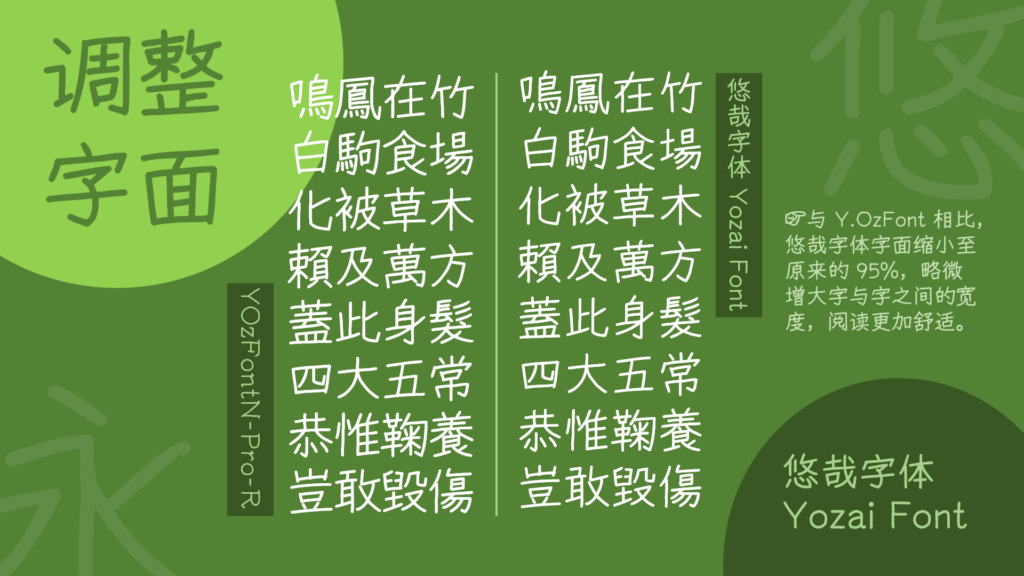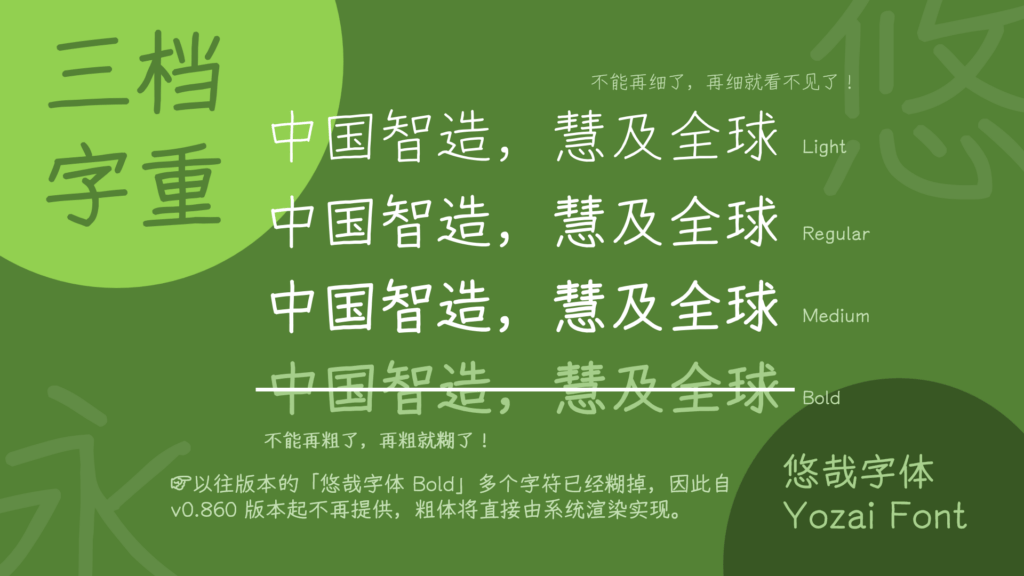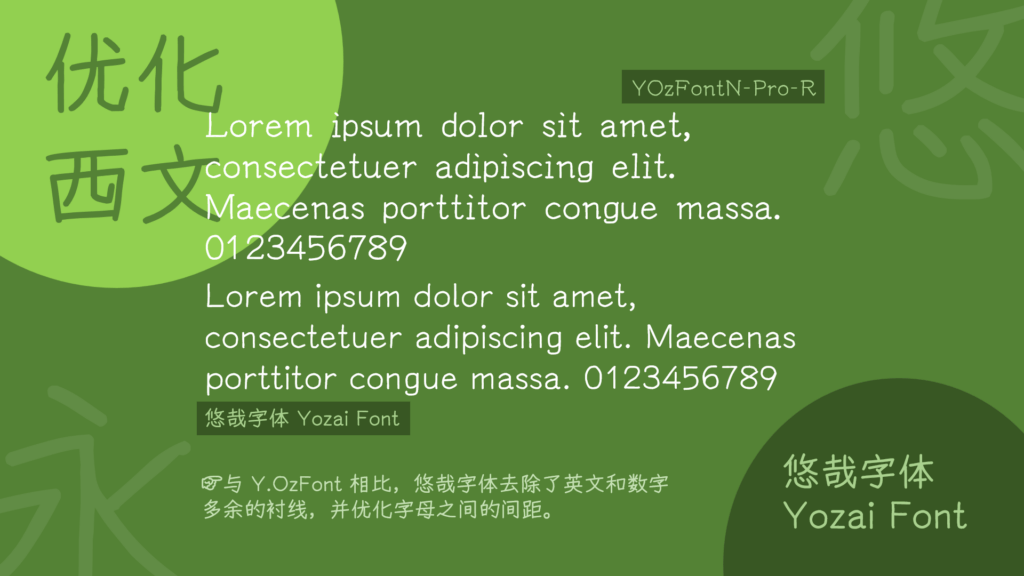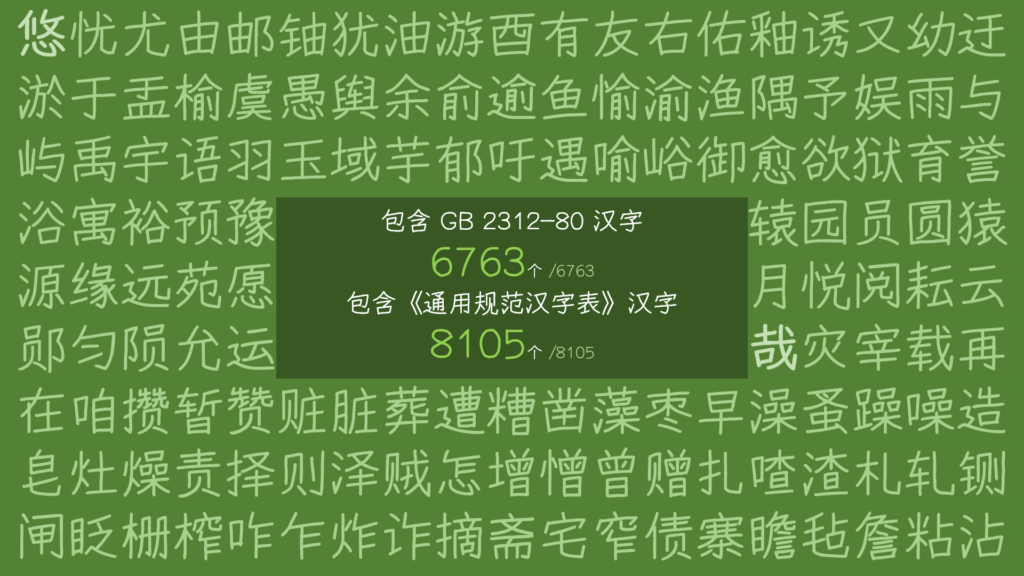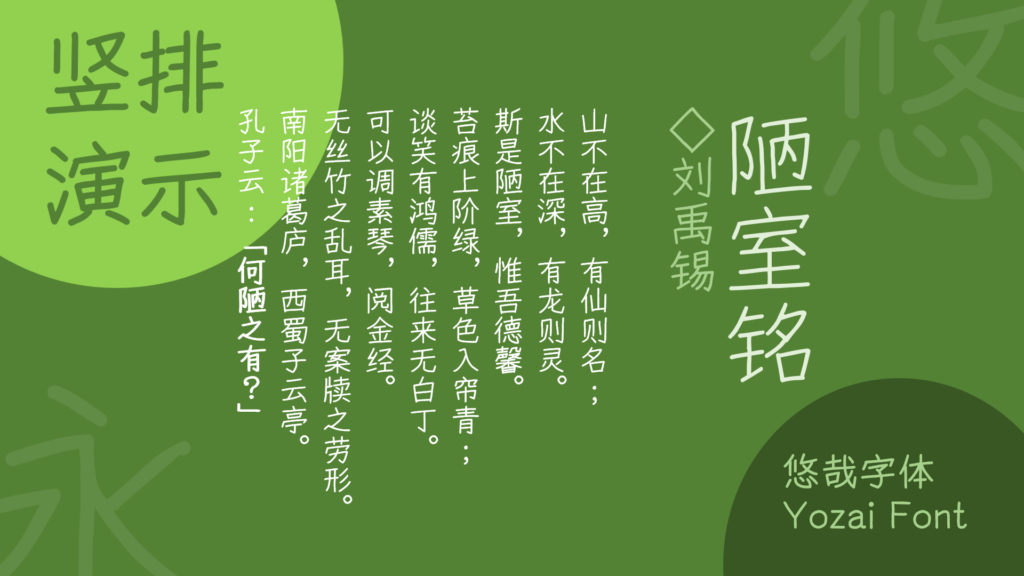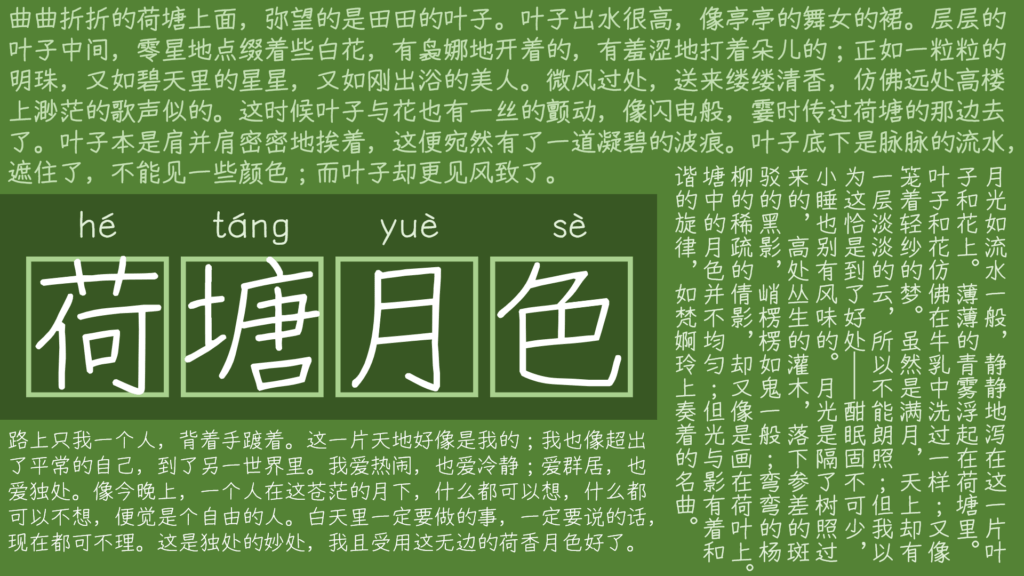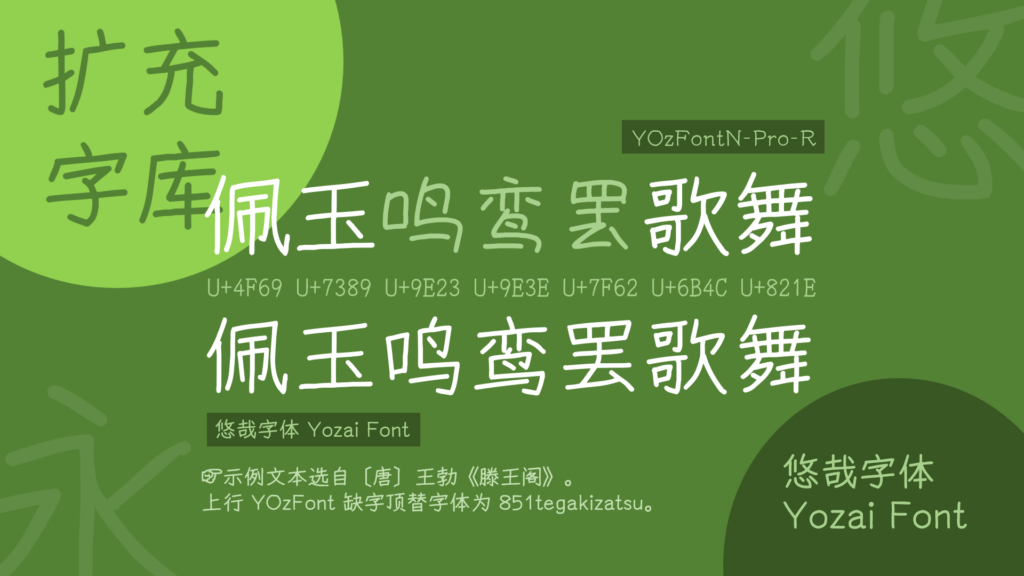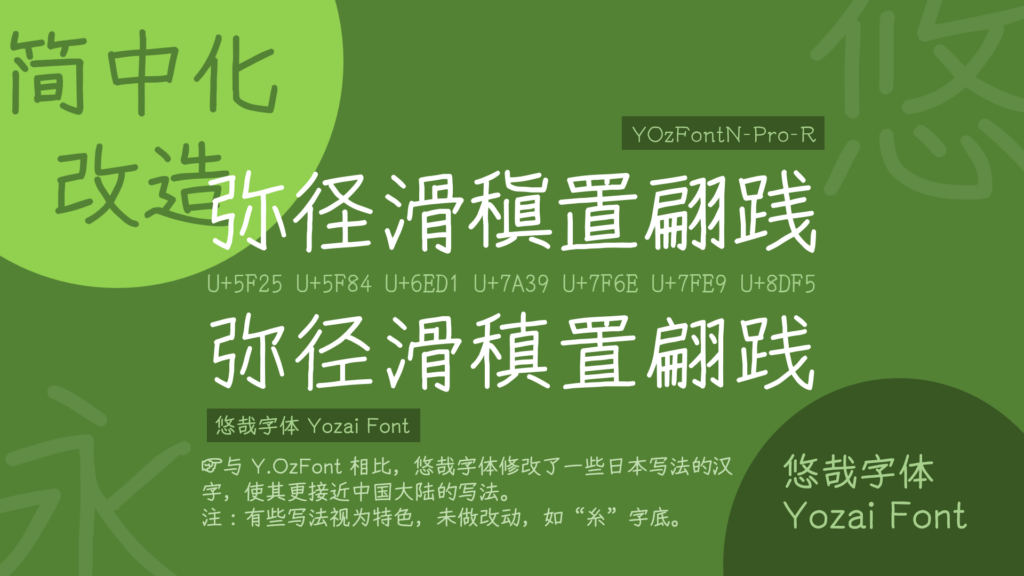
本字体是一款基于 Y.OzFont 的手写风格字体,其开发旨在保留并延伸原有字体的自然书写美感。利用原字体中已有的笔划和部件,通过巧妙的拼接和细致的调整来创造出新的汉字字符,在必要时,开发者也会使用鼠标手绘出所需的部件以确保字形的完整与和谐。目前,该字体已全面补全原字体中具有对应繁体字的简体字、GB 2312 标准范围内的所有汉字(共6763个),覆盖了《通用规范汉字表》中的全部汉字(总计8105个),并包含了 BIG5 编码范围内的所有汉字(多达13058个)。自 0.860 版本起,项目引入了 zi2zi 深度学习模型,用于高效补全 CJK 统一表意文字基本区的 20992 个字符,并根据用户需求,少量增补了扩展区的汉字。 在继承原版 Y.OzFont 风格的基础上,本字体进行了一系列优化:字面整体缩小至原来的 95%,使得排版更为紧凑;同时对西文字母和标点符号的形态进行了专门优化,提升了混排时的视觉协调性;此外,还修改了部分汉字的写法,使其更贴近中国内地的现行规范字形。鉴于原版字形笔画偏细,从 0.715 版本起,新增了 Medium(中等)字重,以满足不同场景下的使用需求。自 0.717 版本起,本字体已发展为包含 Light、Regular、Medium、Bold 四种字重的完整系列;不过,从 0.860 版本开始,为了精简和聚焦,Bold 字重被取消。
霞鹜自制开源字体系列 Vol.2,展示悠哉字体,基于日系手写体 Y.OzFont 修改制作。
悠哉字体 YOzai(YOzFontN-Pro-R)字体展示图,呈现该字体的示例文本“佩玉鸣鸾罢歌舞”,标注了对应字符的Unicode编码,注明示例文本选自唐代王勃《滕王阁》,并说明缺字时的替代字体信息。
该图包含两组汉字字形集合的统计信息:GB 2312–80 标准包含 6763 个汉字,《通用规范汉字表》包含 8105 个汉字。
悠哉字体 (Yozai Font) 简中化改造示例,展示了修改日本写法汉字后的字形效果。
悠哉字体与 Y.OzFont 的对比,展示悠哉字体通过缩小字面和增加间距提升阅读舒适度的效果。
悠哉字体(Yozai Font)的西文优化展示,包含样本文字(Lorem ipsum)、数字0123456789,说明相较于Y.OzFont,去除了英文和数字的多余衬线、优化字母间距。
竖排版式演示,展示刘禹锡《陋室铭》全文,标注所用悠哉字体(Yozai Font)
《荷塘月色》课文摘录,包含标题“荷塘月色”的拼音和汉字,以及朱自清原文段落。
悠哉字体展示四种字重:Light、Regular、Medium、Bold,示例文字为“中国智造,慧及全球”。注:Bold字重在v0.860版本后不再提供。